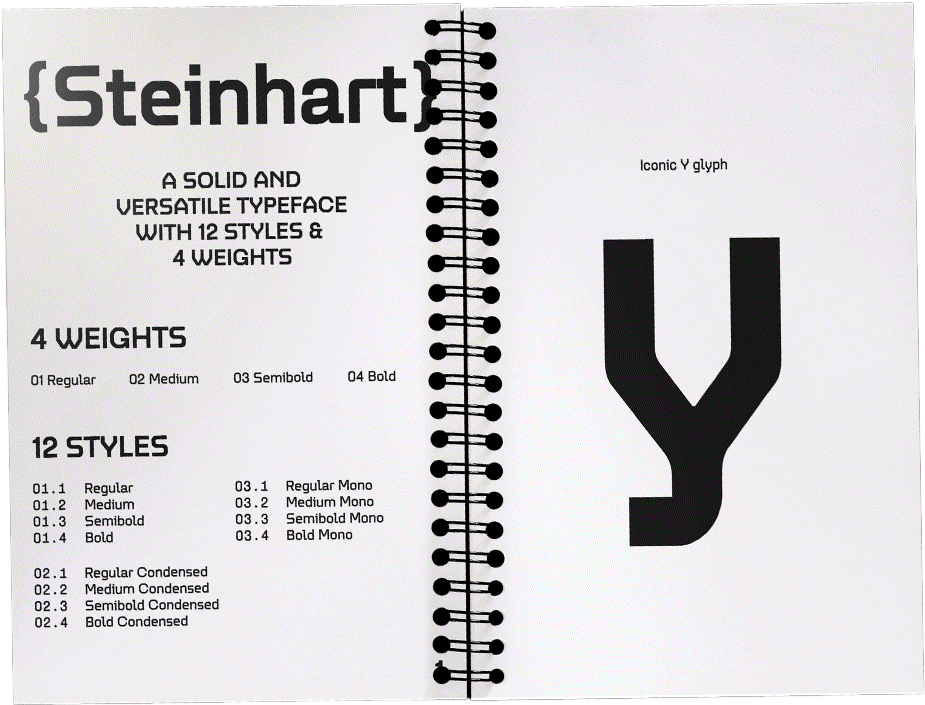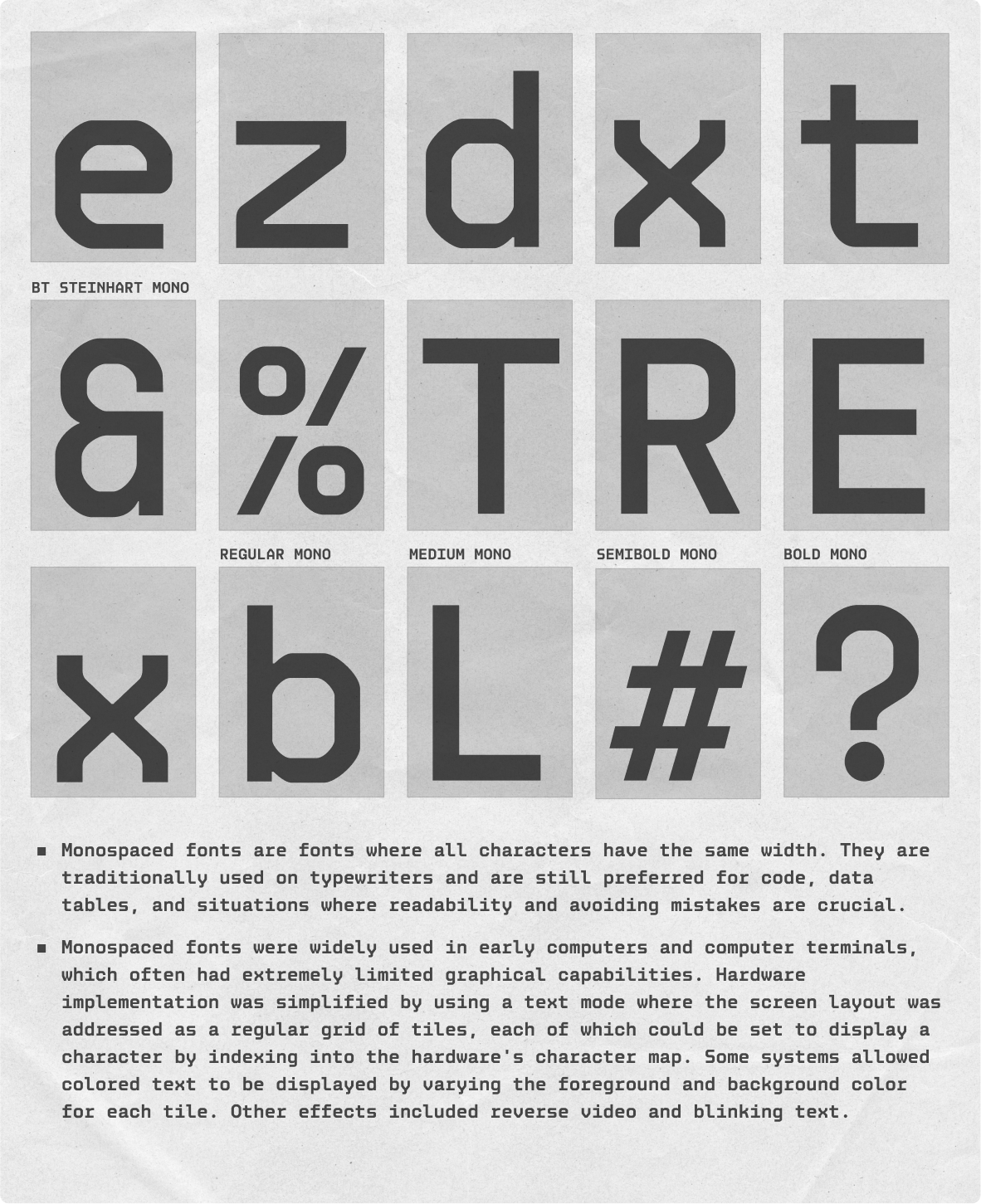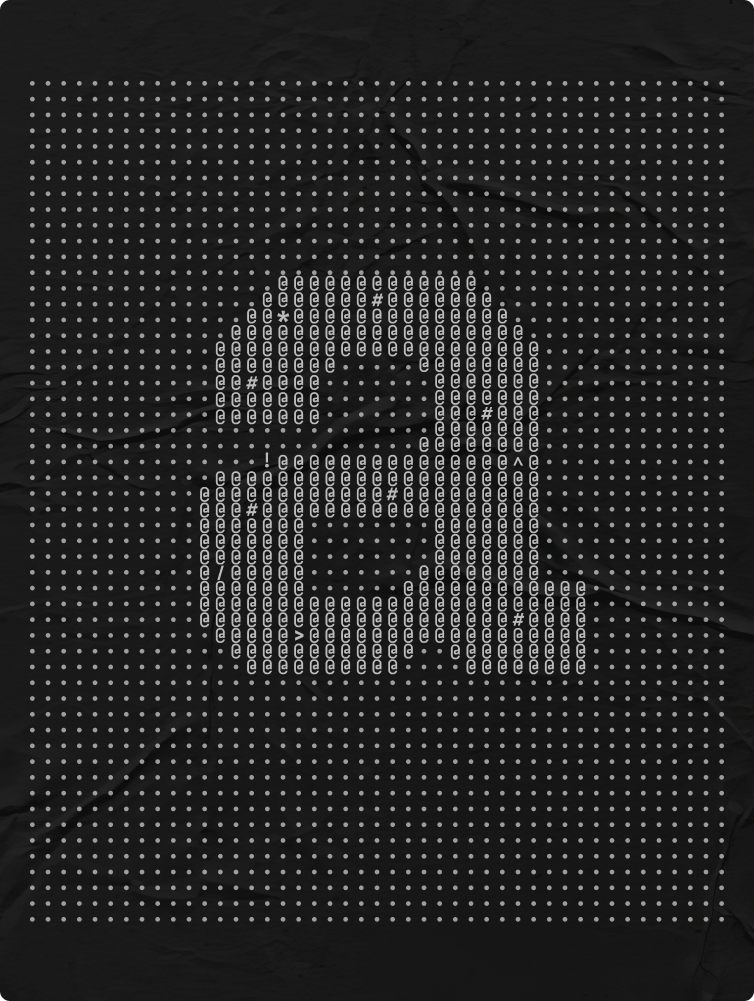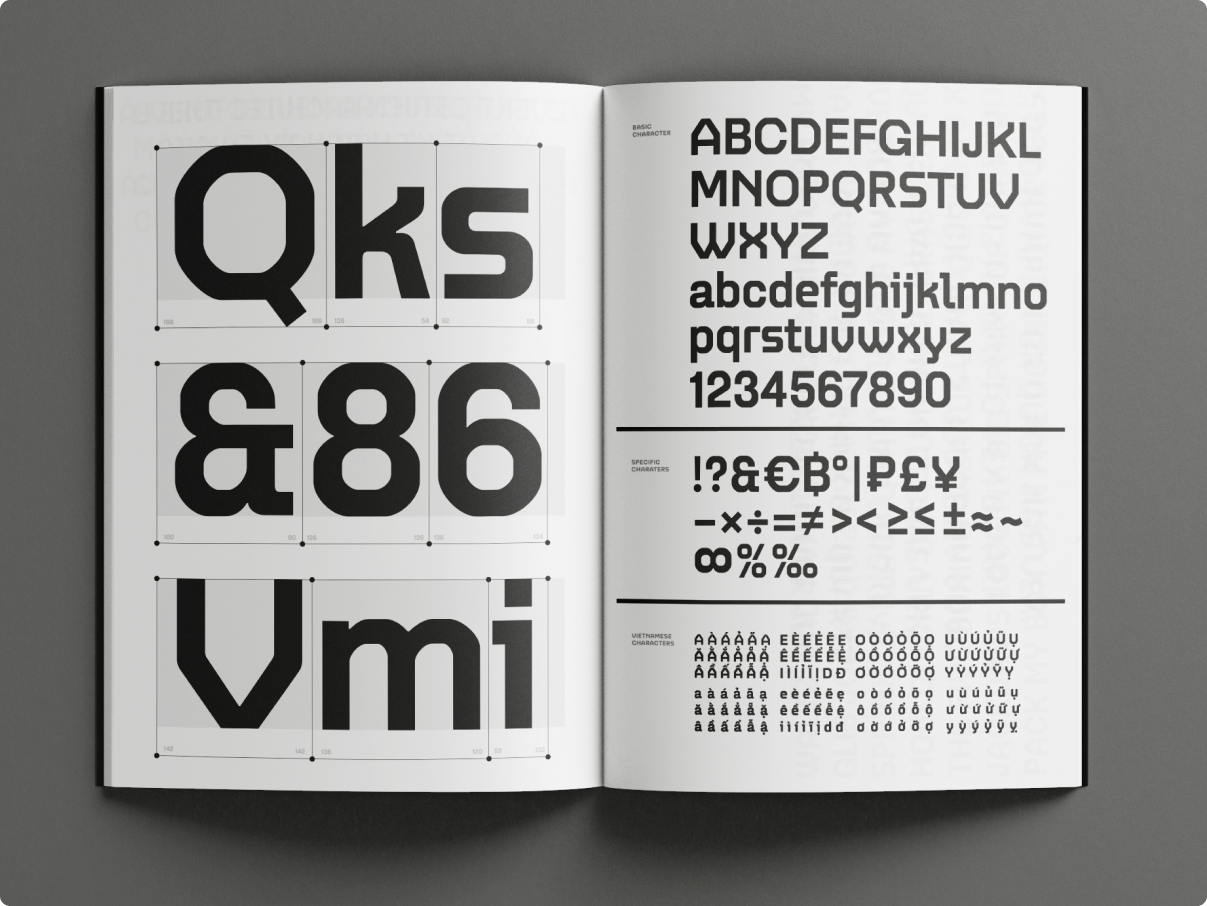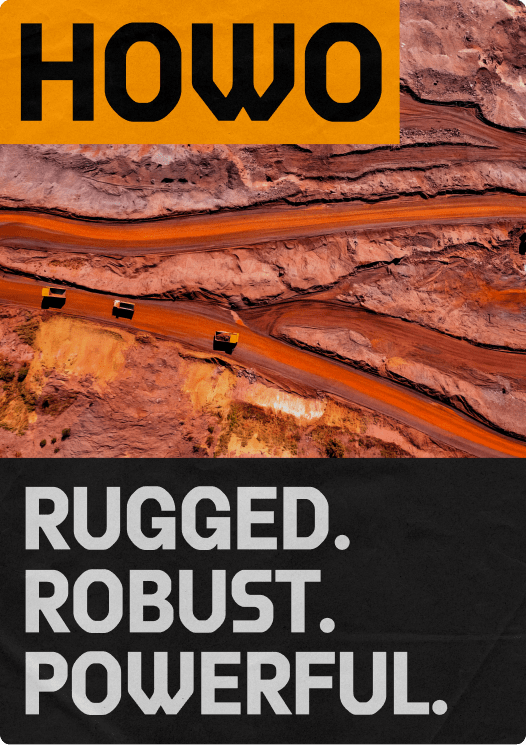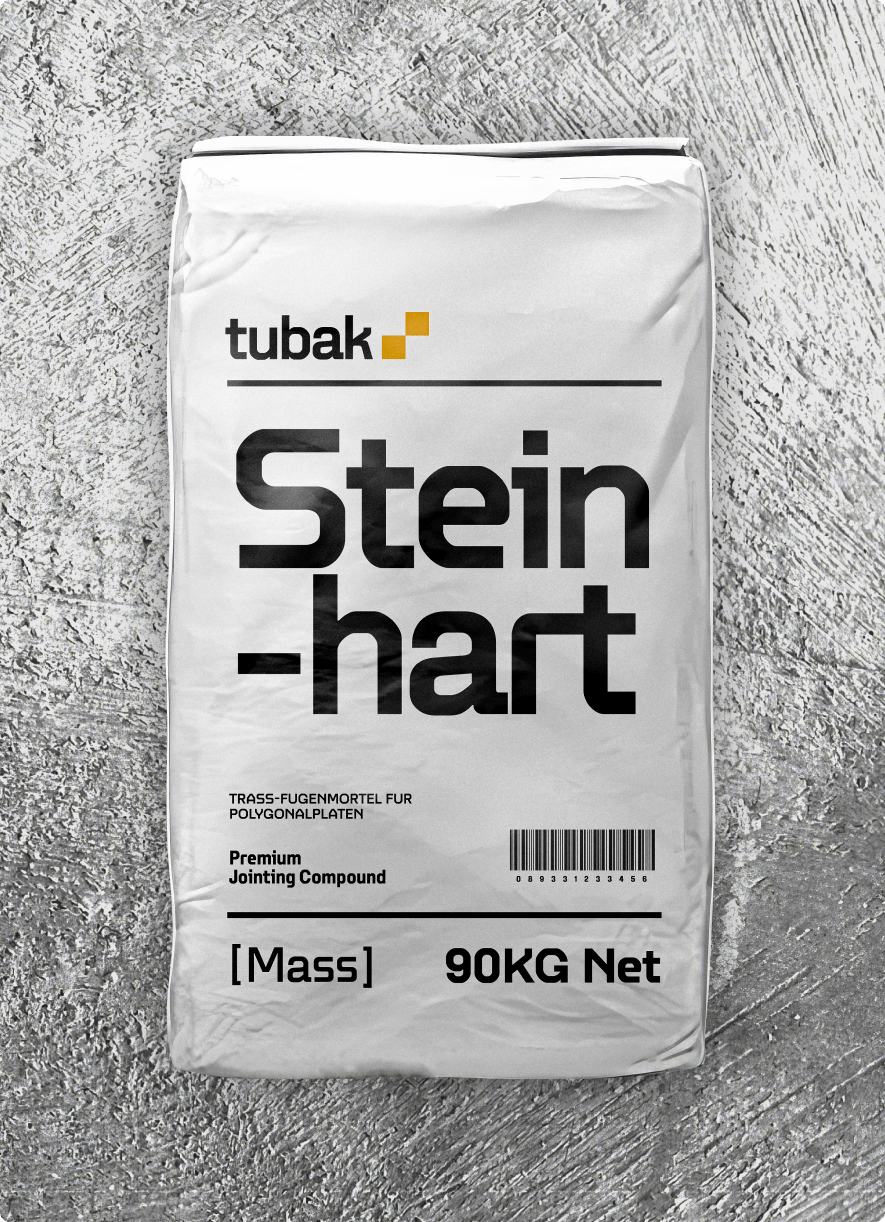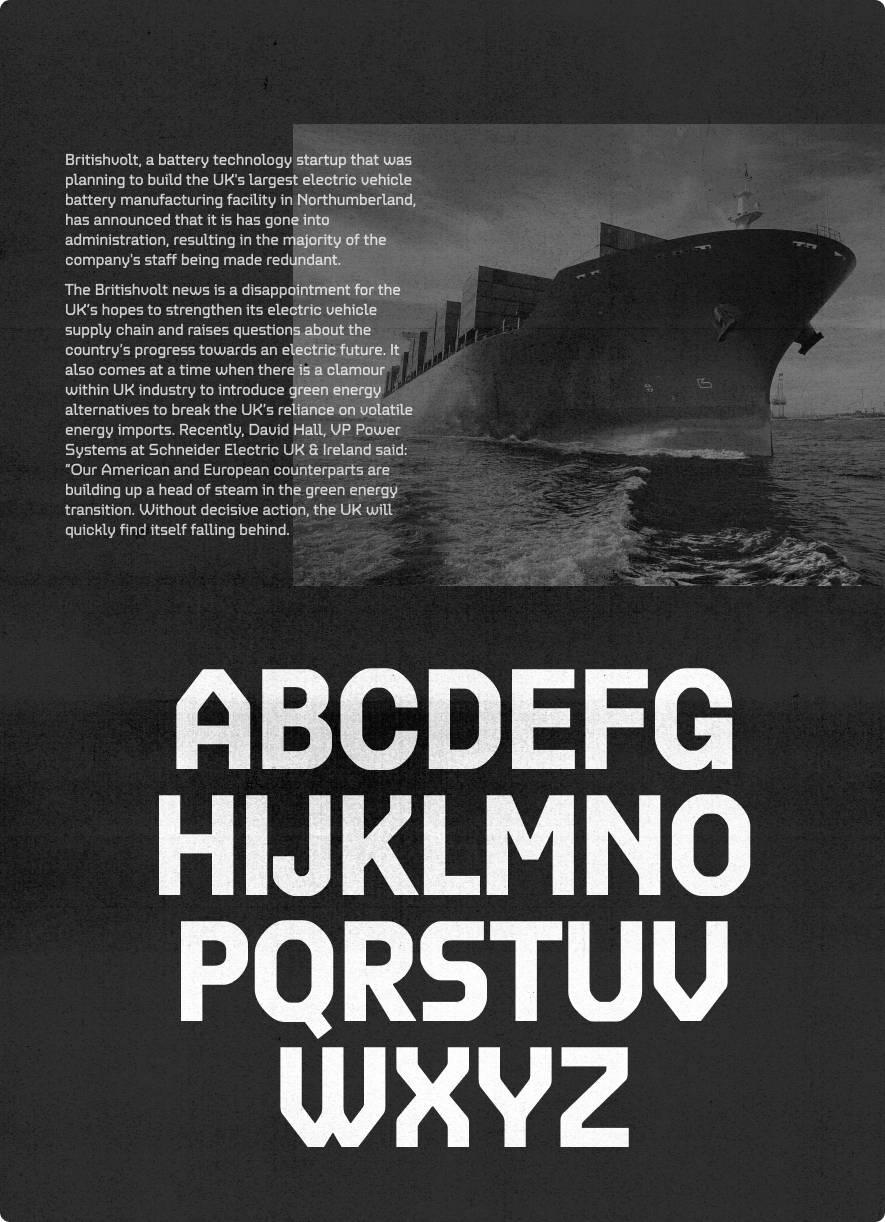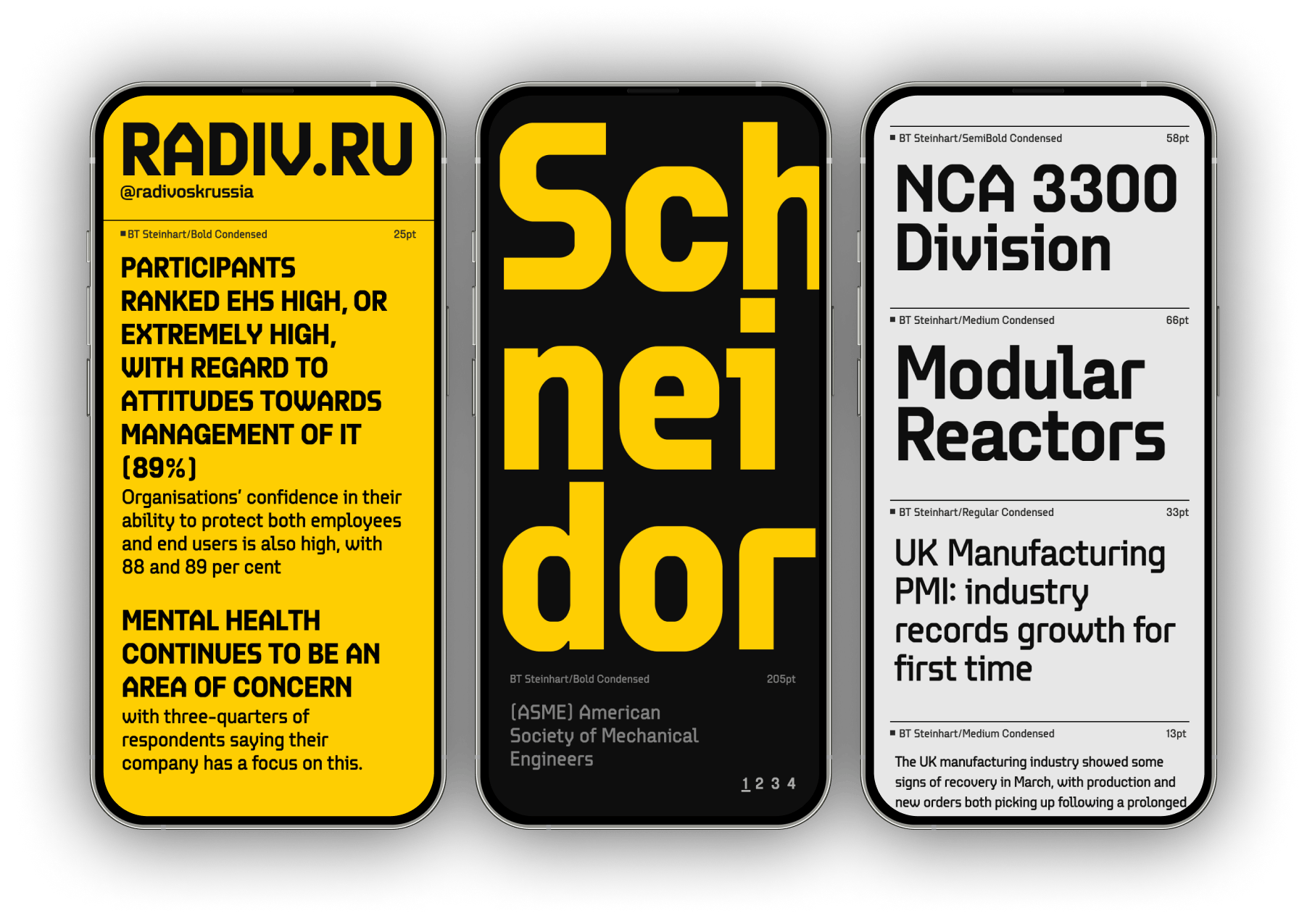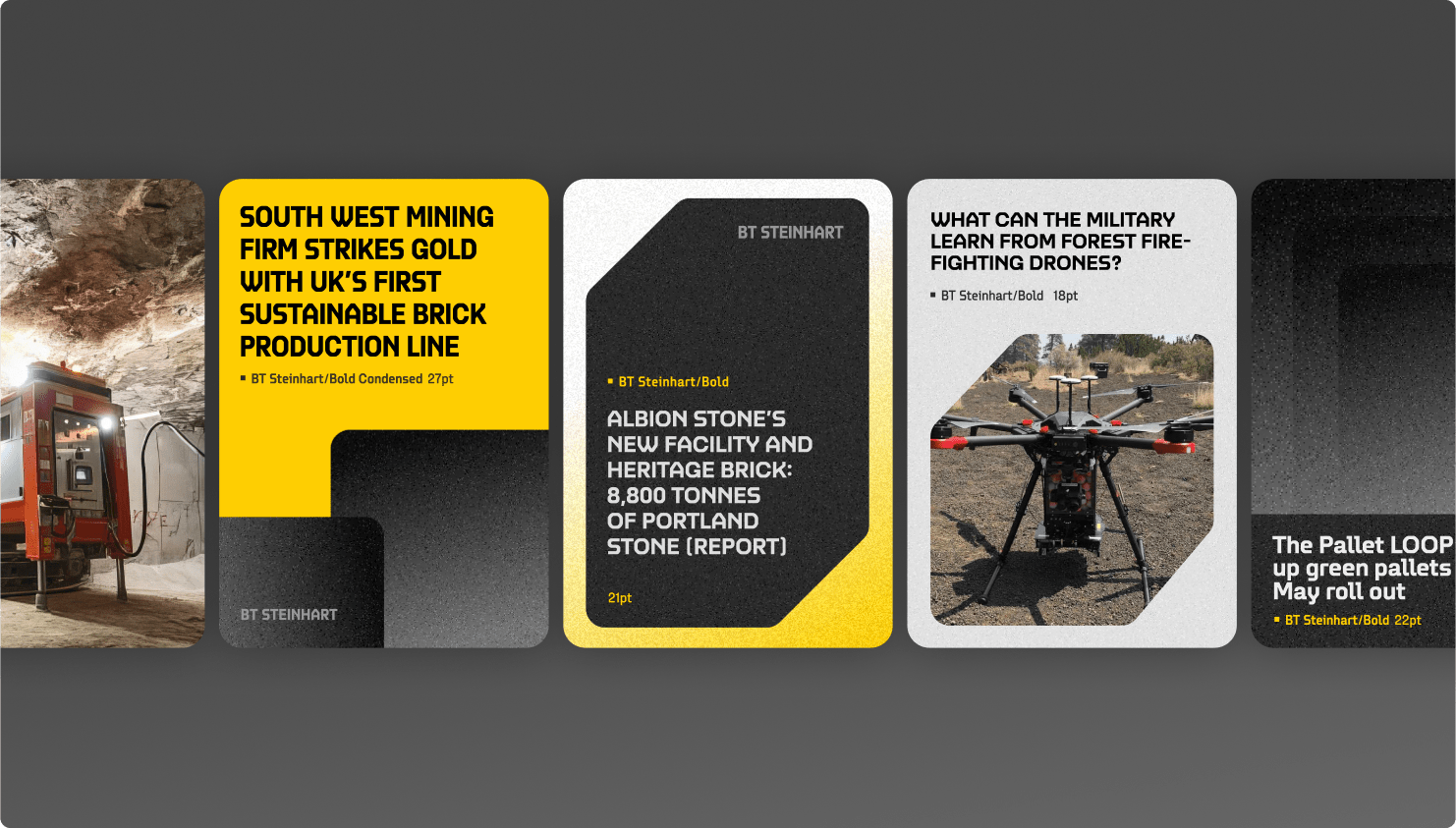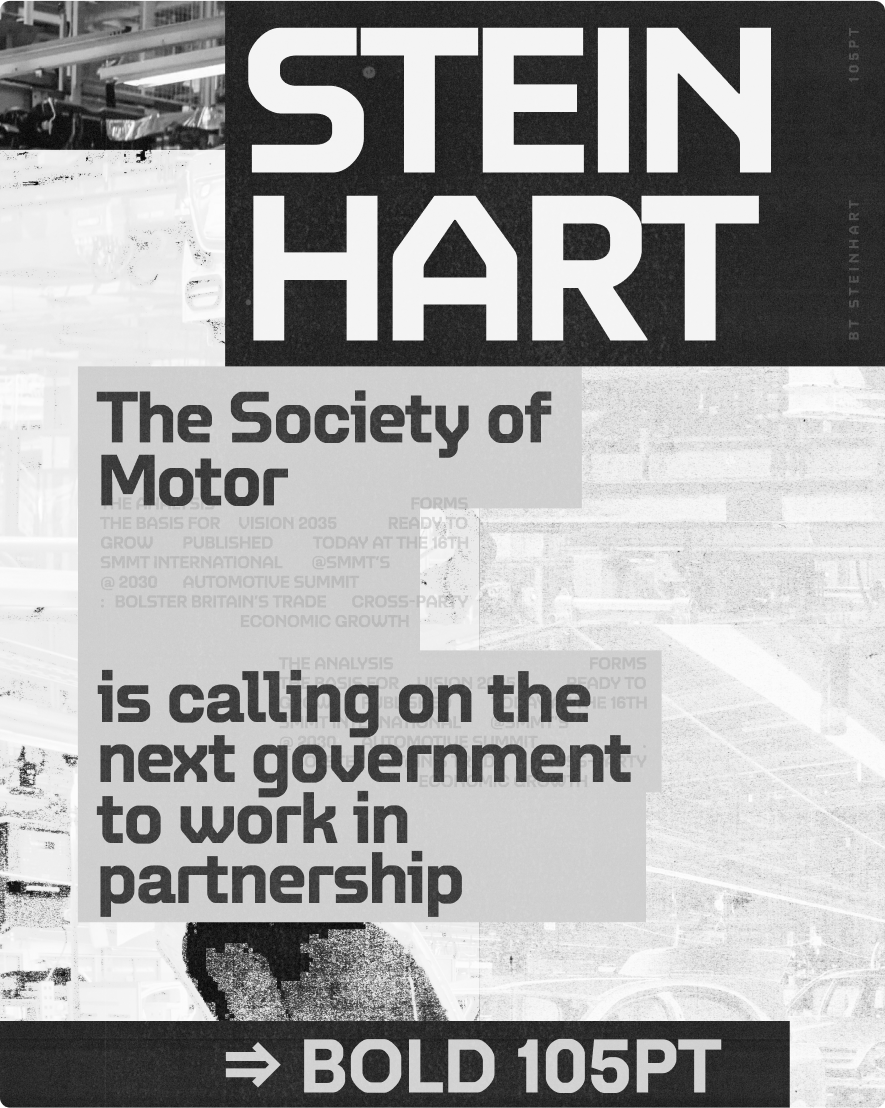
(1) BT Steinhart
BT Steinhart, typeface lấy cảm hứng từ những cỗ máy công nghiệp đồ sộ, mang đến sức mạnh và cá tính cho các dự án thiết kế . Nét chữ vuông vức, mạnh mẽ cùng cấu trúc chắc chắn tái hiện hình ảnh những cỗ máy, trục, bảng điện tử đầy ấn tượng, khơi gợi cảm giác về sự chính xác và tin cậy.
• Collection 3 Families, 12 Styles
• Design Beautype Studio
(2) BT
Steinhart
Mono
Một phiên bản khác - BT Steinhart Mono.
Font chữ Monospace (đơn cách) được sử dụng rộng rãi trên các máy tính và thiết bị đầu cuối thời kỳ đầu, vốn có khả năng hiển thị đồ họa cực kỳ hạn chế. Việc triển khai phần cứng được đơn giản hóa bằng cách sử dụng chế độ text mode, trong đó bố cục màn hình được coi như một lưới các ô vuông đồng đều.
Chúng thường được sử dụng trên máy đánh chữ và đến nay vẫn được ưa chuộng trong lập trình code, bảng dữ liệu và các trường hợp cần đảm bảo khả năng đọc và tránh lỗi.
Character Set
Basic Latin
Vietnamese
Punctuation, Numerals, Currencies
SUPPLEMENTAL ARROWS